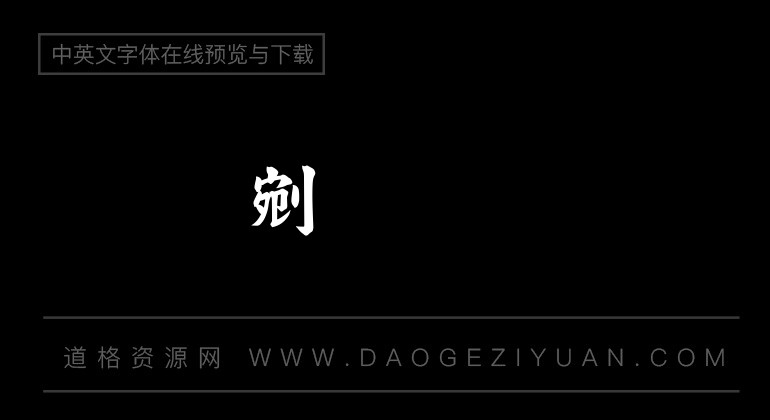
超研泽粗楷
超研泽粗楷是一款超研字体家族中的粗楷体字体,由超研字体设计师汪贤贤精心设计,具有良好的结构和视觉效果。它融合了中国传统楷书的精髓,具有清新的美感,可以用于报纸、杂志、书籍、海报、宣传单等印刷品的设计,从而提升印刷品的视觉效果。
超研泽粗楷是一款非常不错的手写艺术字体,具有很好的视觉感,适合于文化类的宣传设计、商业类品牌的广告和产品包装设计以及个性化文字排版等较多场景。